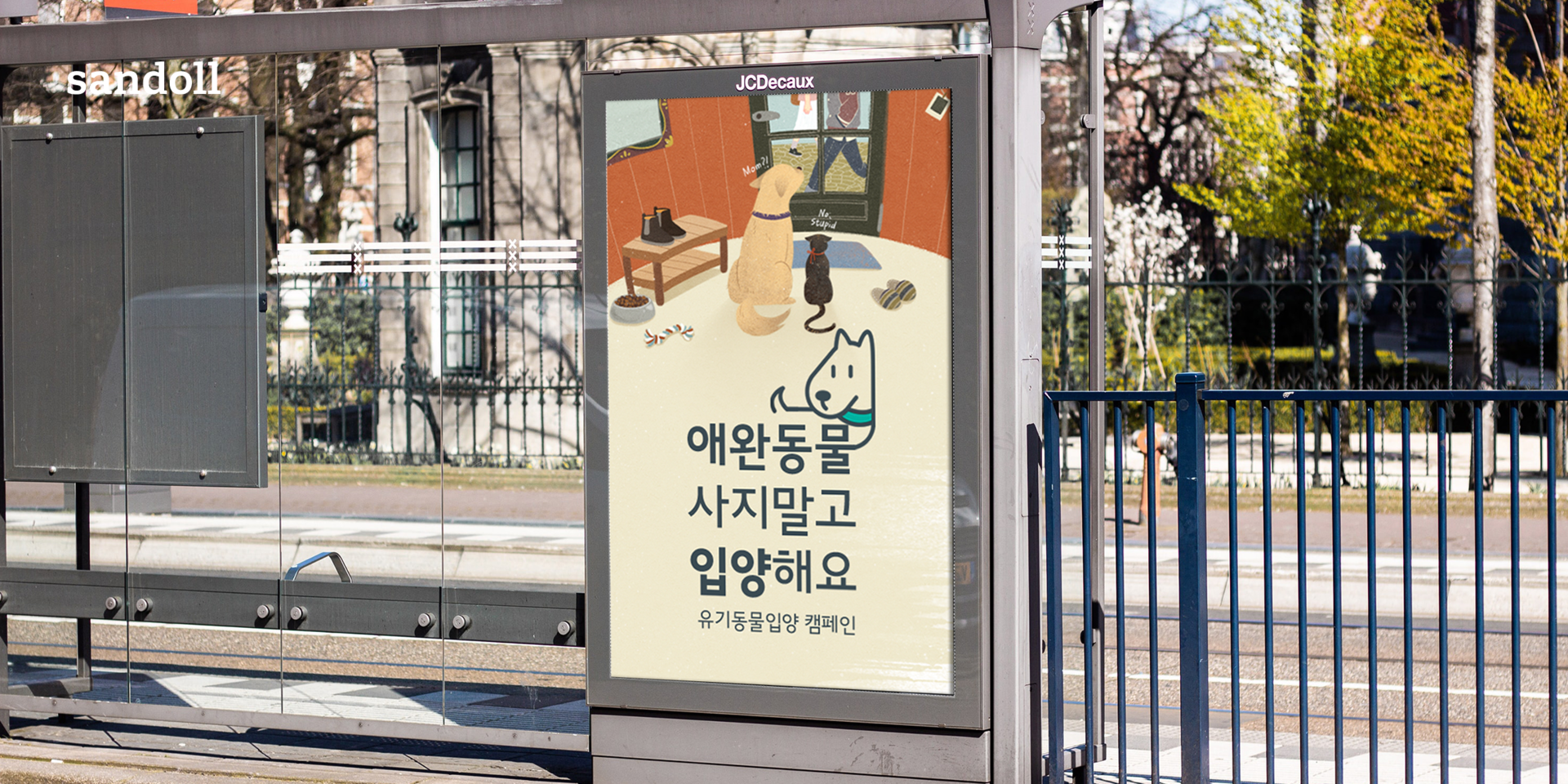
Sandoll 고딕Neo3
산돌 고딕Neo3는 다양한 웨이트의 슈퍼 패밀리를 갖춘 프리미엄 고딕 폰트이다.산돌의 기술과 경험을 집약한 프리미엄 본문서체 Sandoll Neo Series의 일환으로서 기존 산돌 고딕의 고전적인 모습에서 현대적인 세련됨이 돋보이도록 디자인하였다.사용자 중심의 설계로 사용성과 가독성을 최우선으로 고려하였으며 Neo Series 중 가장 모던한 스타일의 탈네모꼴 형태로 젊고 진보적인 감각을 느낄 수 있다.